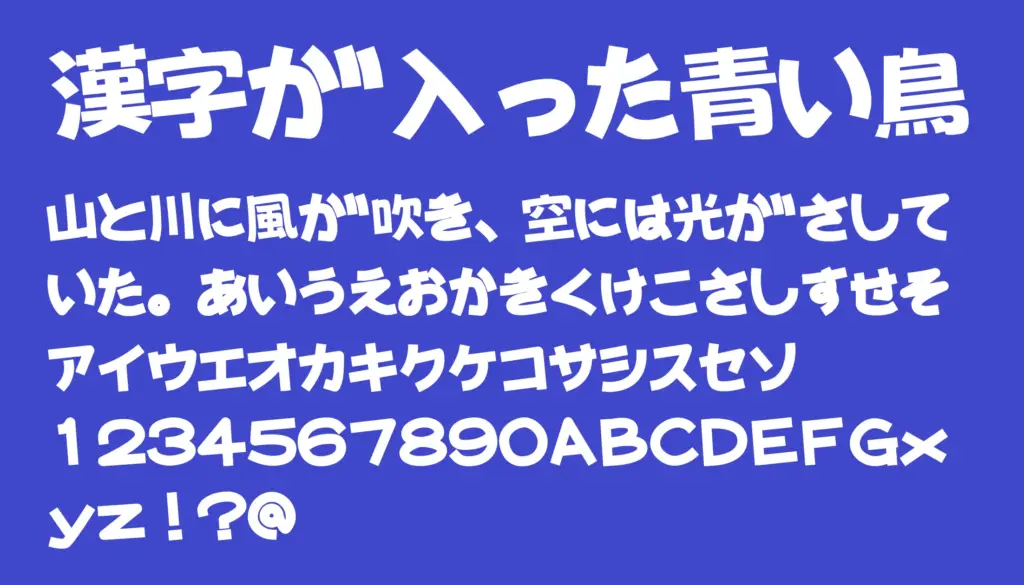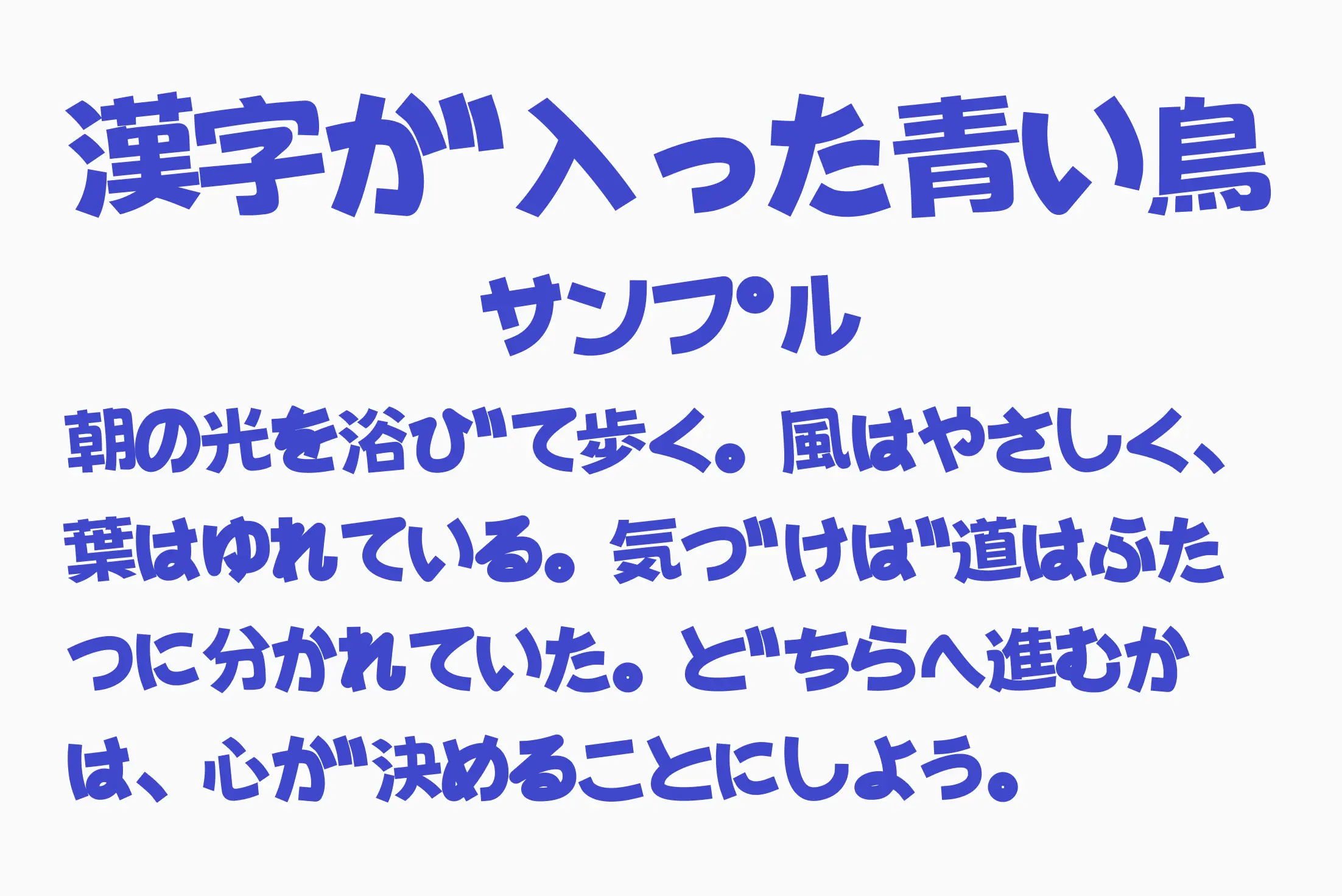
どこか懐かしく、あたたかみのあるレトロな雰囲気が魅力の丸ゴシック系フォントです。文字の柔らかなカーブと程よい太さが、親しみやすく優しい印象を与えてくれます。チラシやショップツール、パッケージデザインなど、日常の中で気軽に使えるバランスの取れたデザイン。ひらがな・カタカナ・漢字を収録し、文章の表現力も高く、レトロポップな世界観を演出したいときにぴったりです。
漢字が入った青い鳥